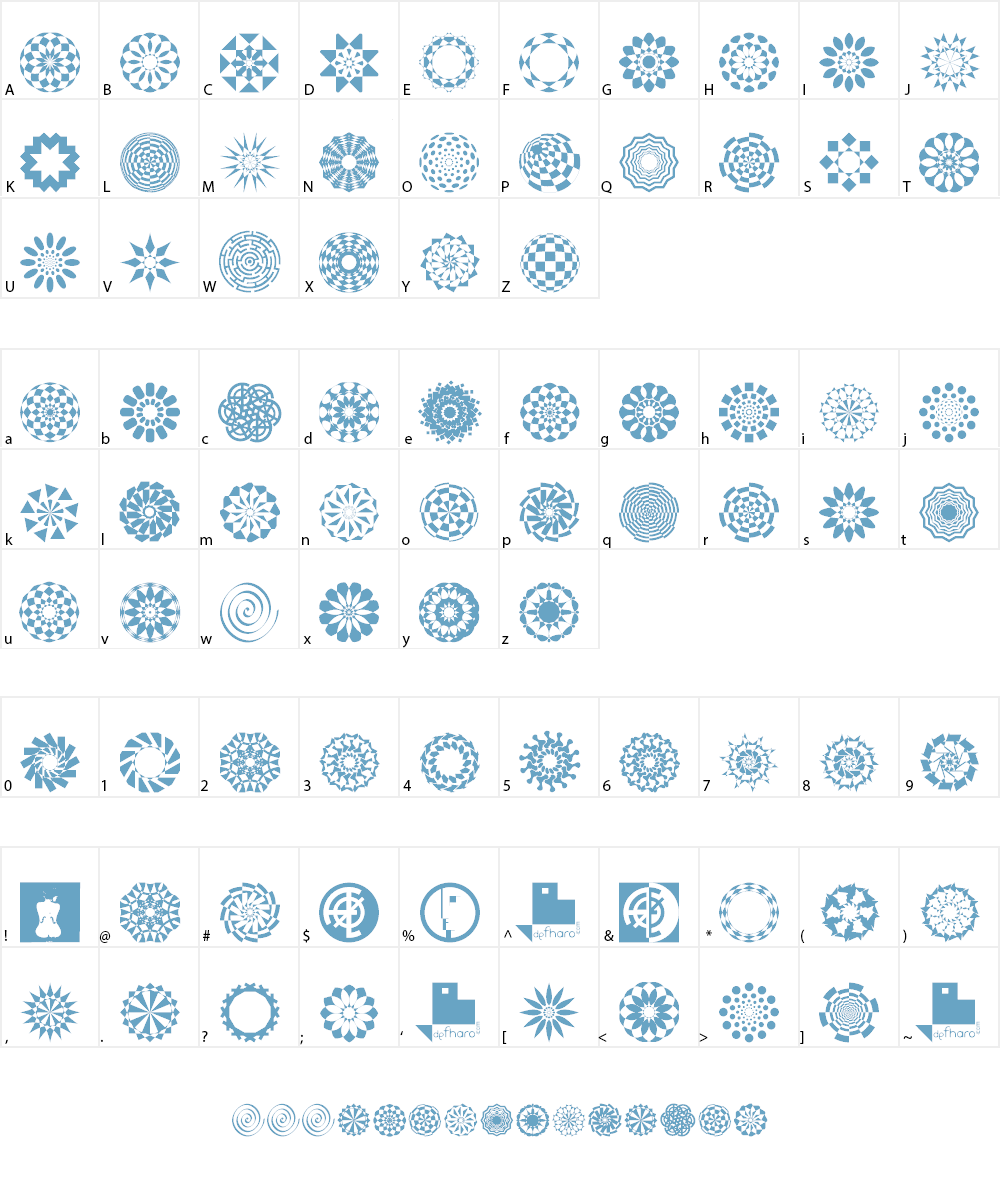
ta colección de Clip art ha nacido de formas geométricas básicas y complejas moviéndose sobre el círculo, además esta inspirada en los diseños de la colección de relojes de diseño ÆØ Watches “The only one collection”, más concretamente a la serie Op-art creada por mí al final de los 80.